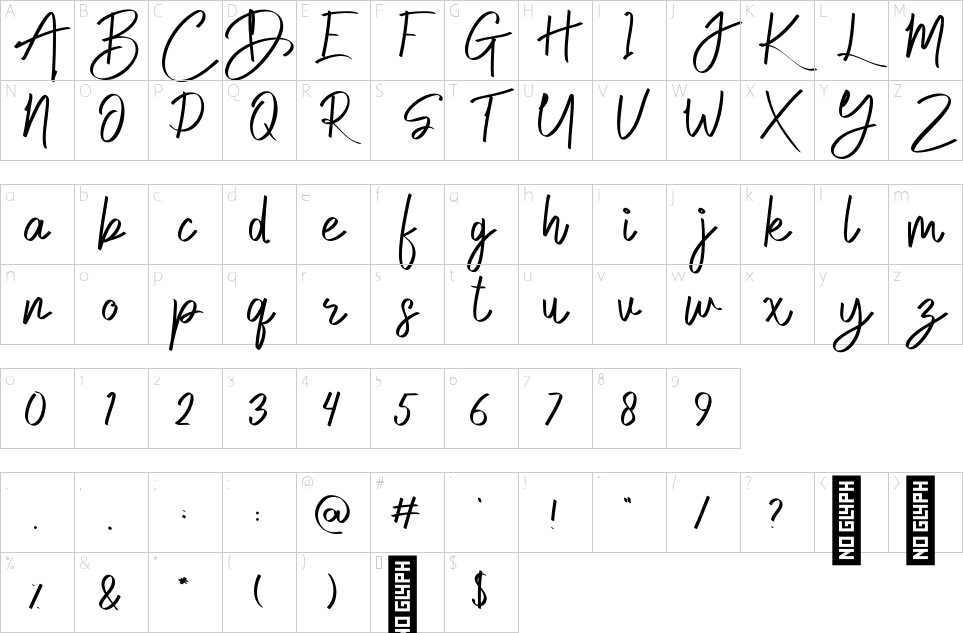
Descubra a caligrafia Gentle Dad para personalizar seu layout com uma estética suave e elegante. Desenvolvida pelo designer helotype, esta fonte está disponível gratuitamente tanto para Windows quanto para Mac. Com um estilo amigável e relaxado, Gentle Dad é perfeito para criar mensagens de texto envolventes, designs gráficos agradáveis ou até mesmo artesanatos personalizados. Sua popularidade crescente não tem igual – Gentle Dad foi baixada 1,335 vezes apenas desde sua disponibilização. Que tal adicionar um toque suave e sofisticado ao seu próximo projeto com Gentle Dad?